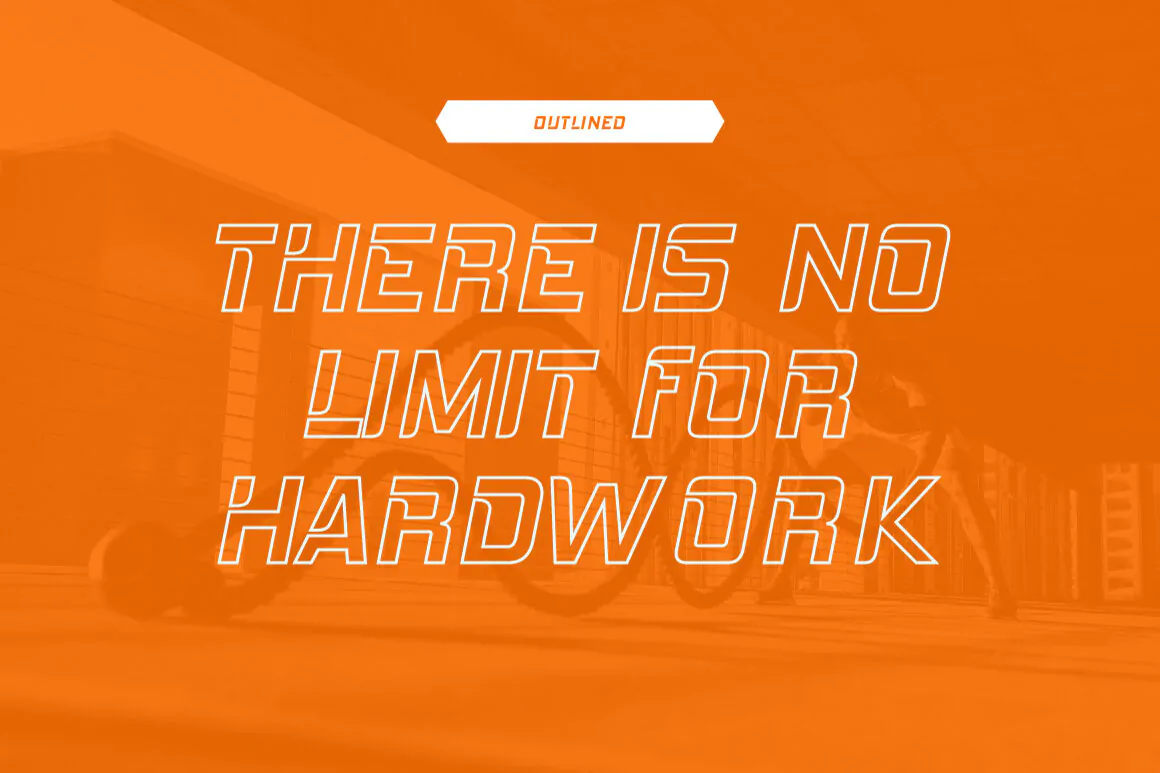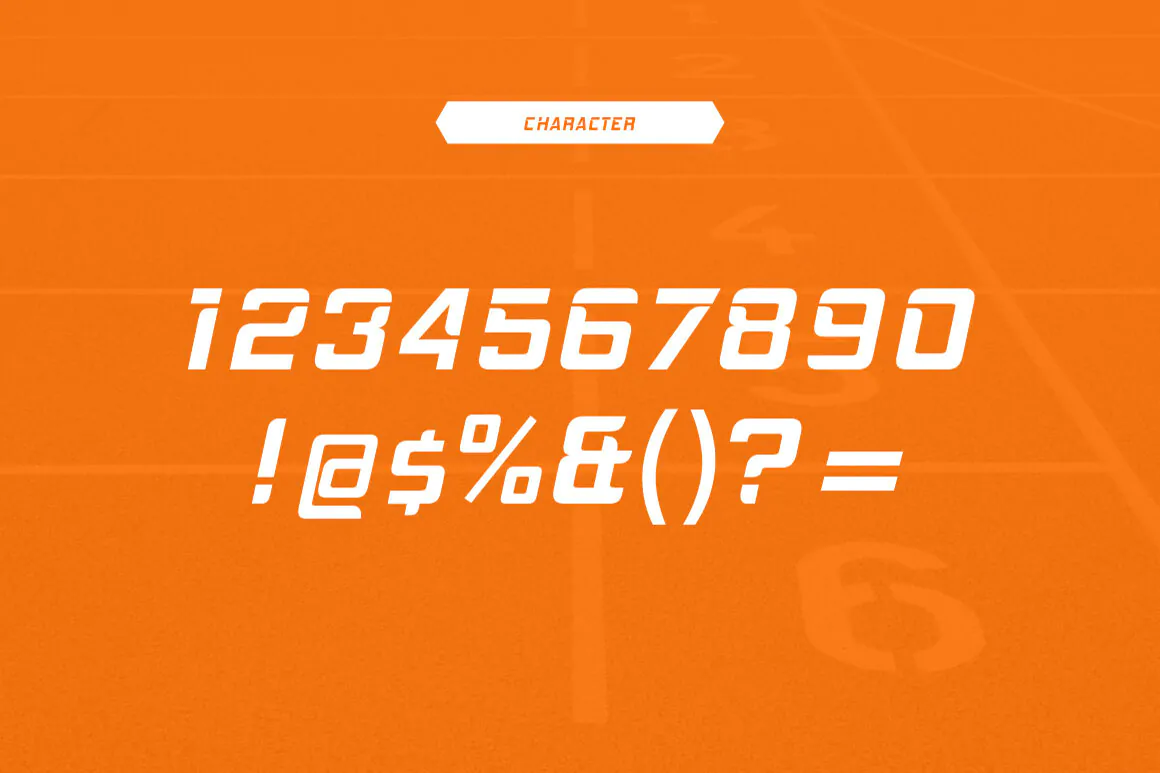
فونت اسپورت طراحی لوگو Tercepat
فونت اسپورت طراحی لوگو
فونت اسپورت طراحی لوگو Tercepat یک قلم فوق العاده زیبای انگلیسی است که به صورت حروف شکسته و برش خورده طراحی شده است و مناسب برای استفاده در پروژههای مختلف به خصوص طراحی لوگو میباشد.